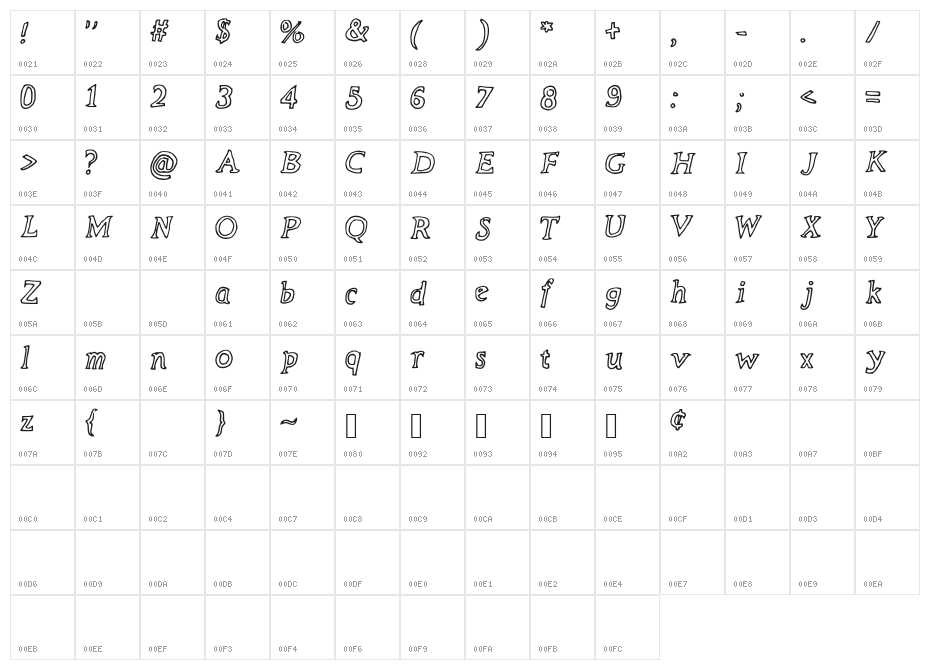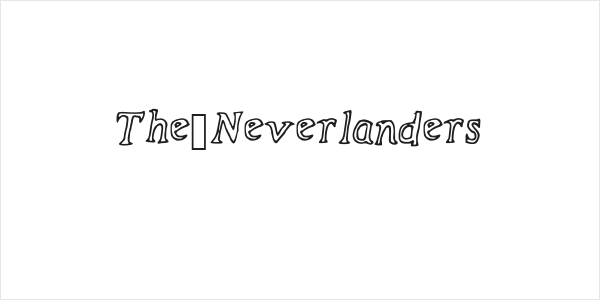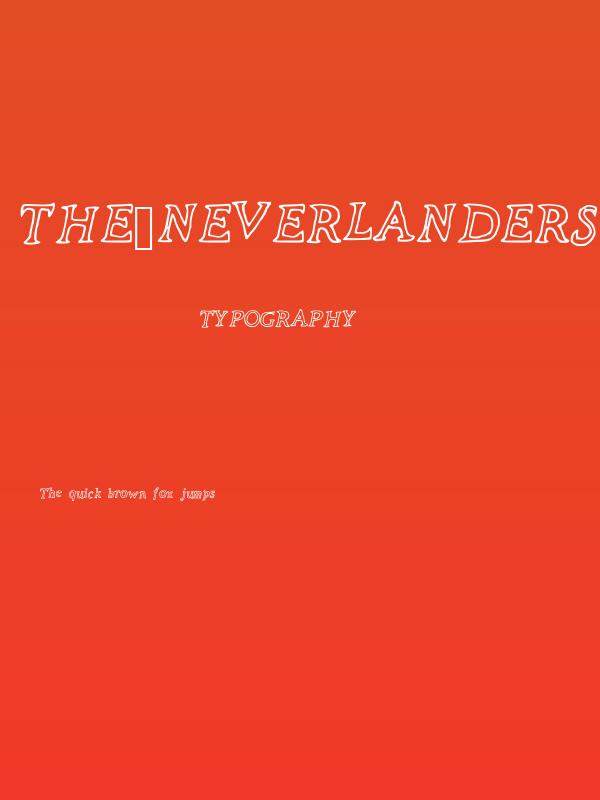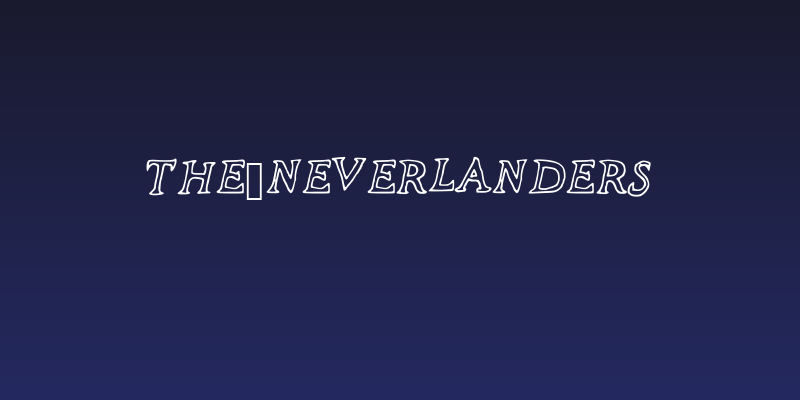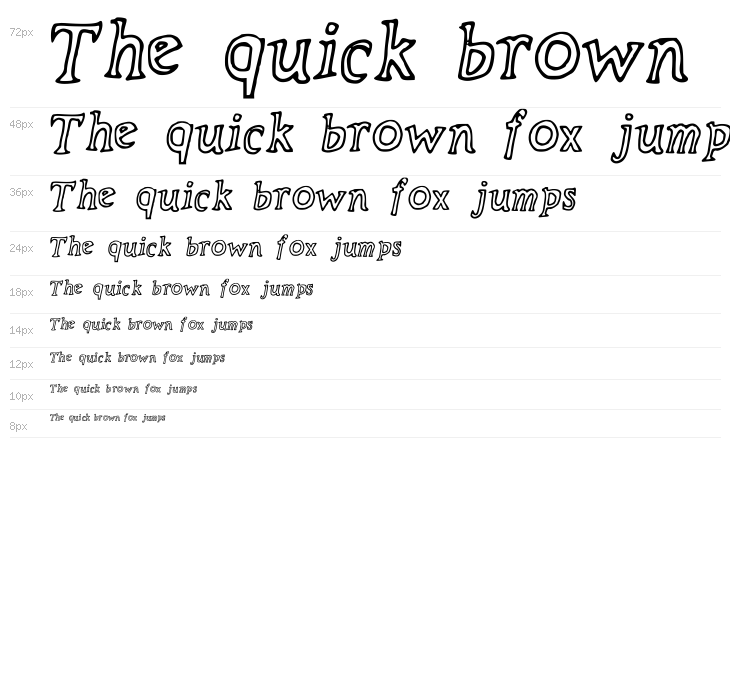
The_Neverlanders Font
| Stile generale | Playful, Whimsical, Fantasy |
| Progetti proposti | Ideal for children's books, fantasy-themed posters, playful branding, and creative invitations. |